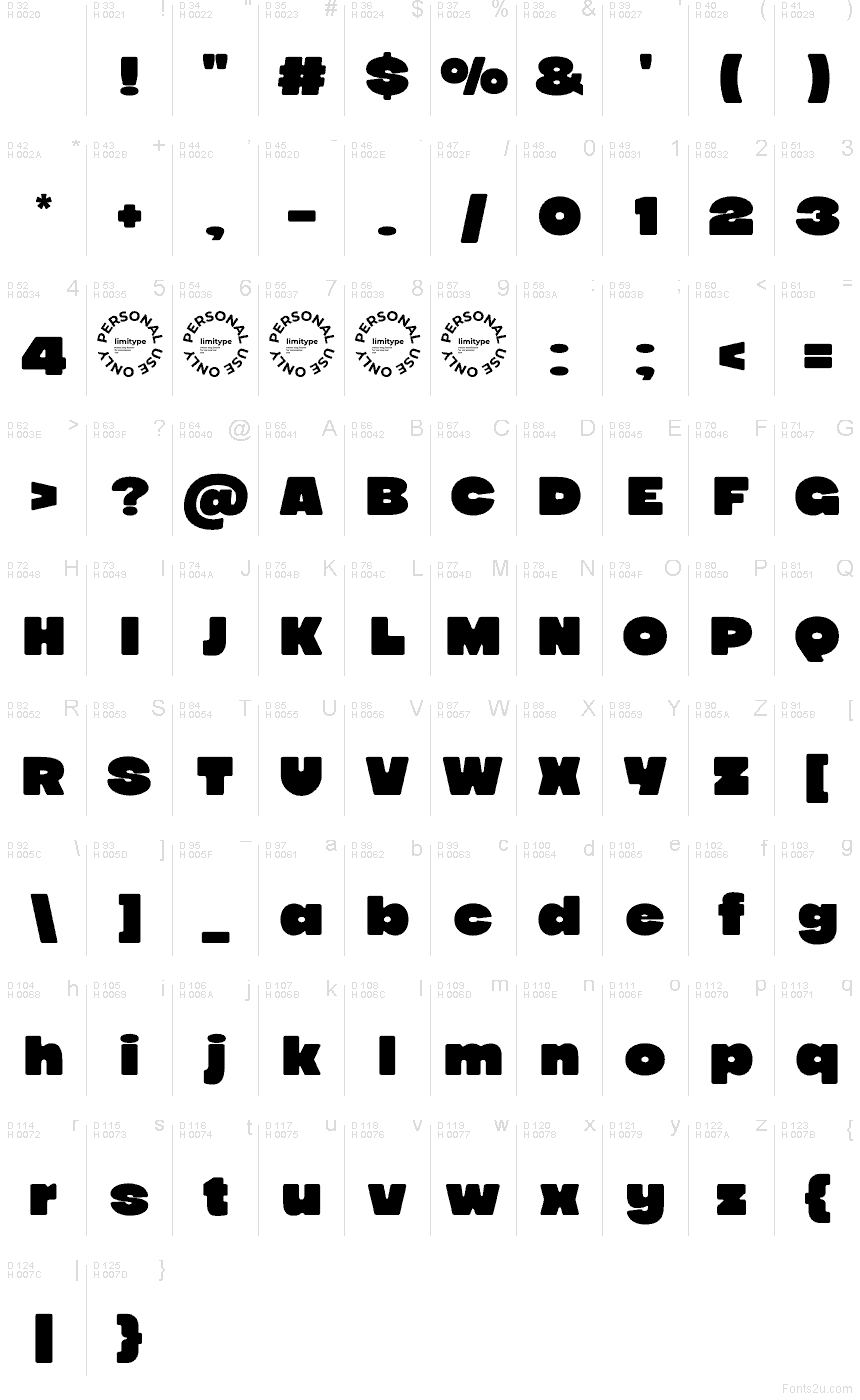
Grovio Bold da Limitype é uma fonte display sem serifa gratuita e encorpada, construída a partir de formas amplas e arredondadas. Suas letras densas utilizam contraformas compactas e junções retas e suavizadas, criando uma silhueta macia, porém marcante. As formas são bem compactas e transmitem uma simplicidade quase lúdica, semelhante a brinquedos.
Em embalagens de alimentos e identidades visuais para o público jovem, o letreiramento volumoso pode transformar qualquer nome em um emblema amigável. Esse mesmo peso também funciona muito bem em produtos musicais e elementos gráficos de jogos, nos quais as formas avantajadas atuam como blocos visuais sólidos em vez de mero texto neutro. Cartazes e publicações infantis são outro destino natural, especialmente quando a tipografia divide espaço com ilustrações simples em estilo cartoon.